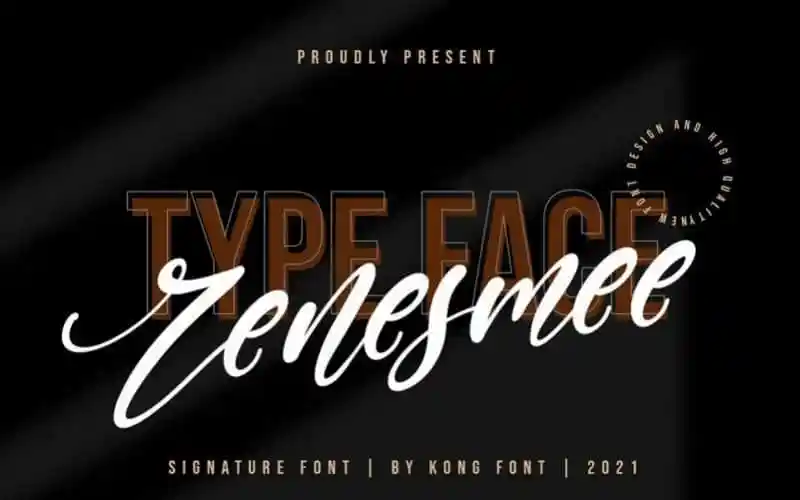
Renesmee Script Font – Download Grátis
A Renesmee Script Font é uma bela tipografia de calligrafia lançada pela Kong Font. Esta fonte é perfeitamente adaptável para projetos românticos como marcas de marca e convites de casamento, além de qualquer outro projeto que precise de um ar delicado e elegante. Ela vem com duas variantes: regular e itálica, oferecendo uma grande variedade aos designers. Não menos importante, suporta várias línguas, garantindo a compatibilidade em todos os tipos de softwares, incluindo aqueles que não são opentype suportados. Como resultado, é uma fonte fácil de usar e versátil para qualquer projeto, seja ele simples ou sofisticado.